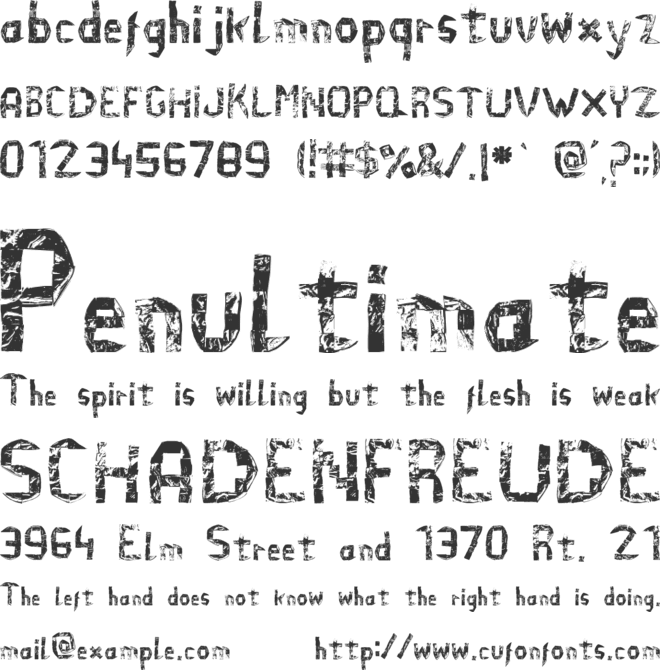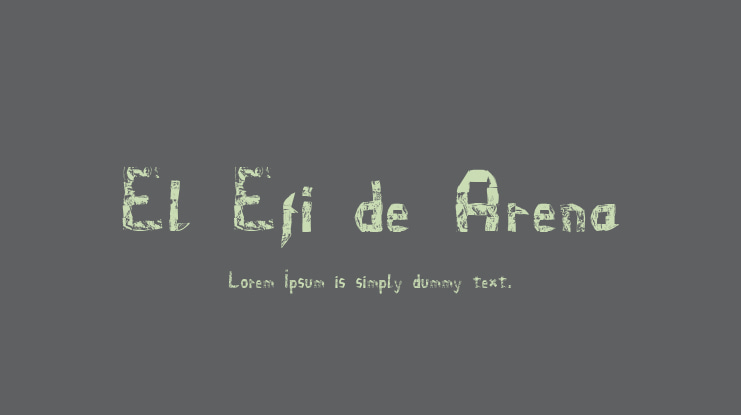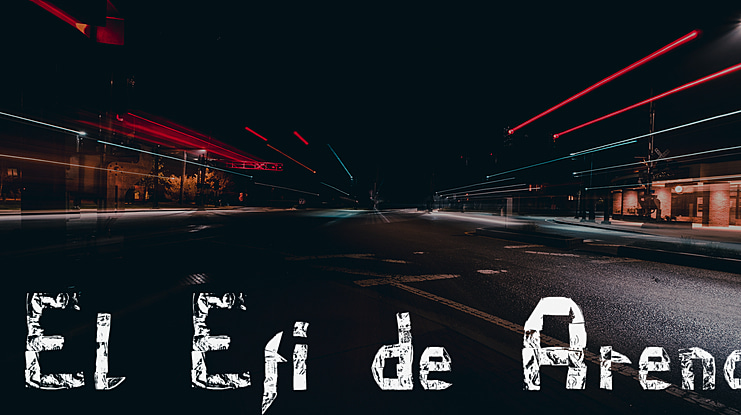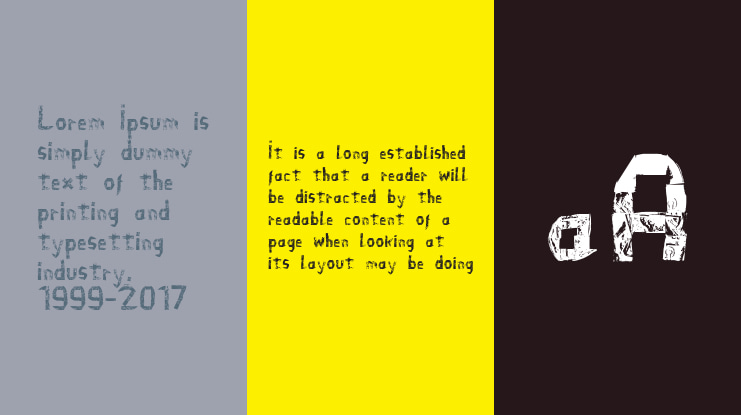
El Efi de Arena Font
JosŽ Ram—n Fuentes y David Gonzalez Guillot
A todo el mundo le gusta recibir premios, pero destrozarlos es un gustazo. Y mucho más si es para repartir el premio entre todas las personas que lo hicieron posible.
Con esos trocitos creamos esta fuente artesanalmente letra a letra.